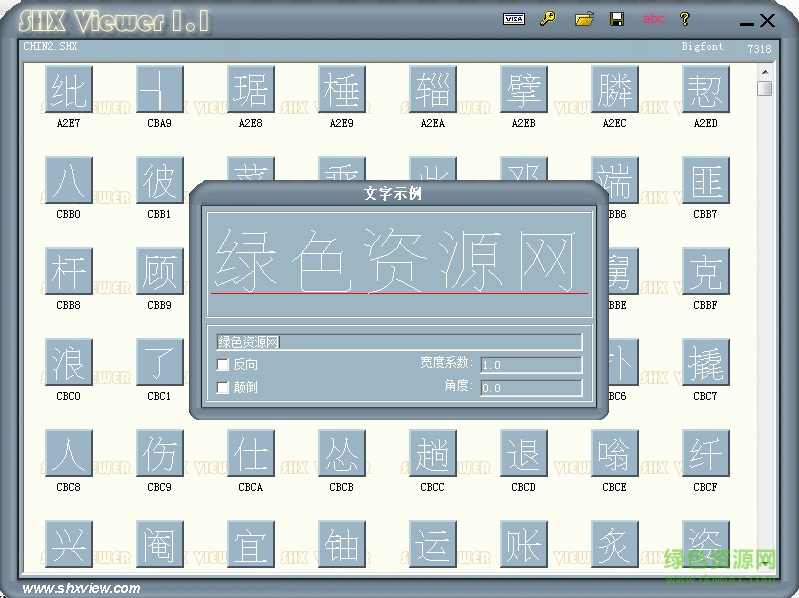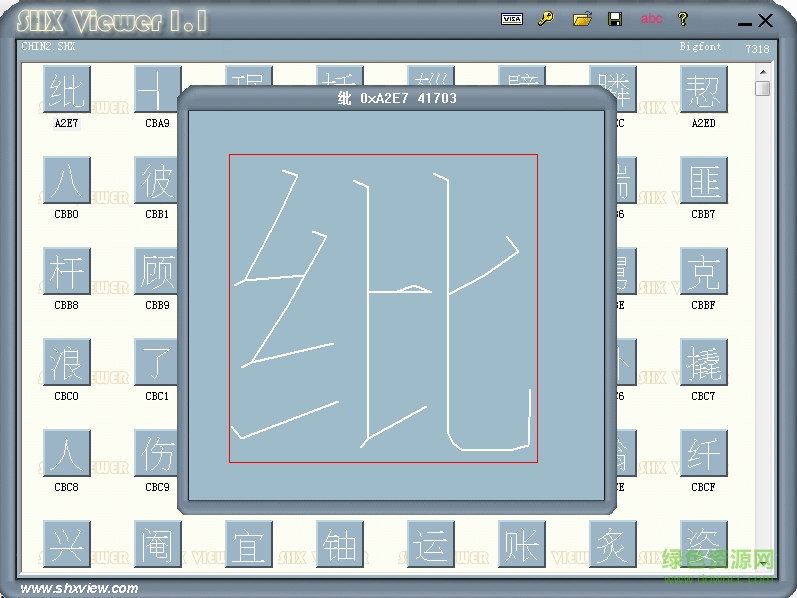
chin2.shx是一款字跡纖秀、簡潔舒適的cad字體,讓你的設(shè)計充滿干凈優(yōu)雅的視覺體驗(yàn),喜歡的朋友來綠色資源網(wǎng)免費(fèi)下載吧!
chin2.shx支持中文輸入,安裝適用于autocad軟件,清新簡約的筆觸深顯造型干練流利之美,適用于平面設(shè)計、創(chuàng)意設(shè)計等領(lǐng)取。
cad里所稱的shx字體和大字體(也叫bigfont),都是autocad自己專用專有的字體。大字體也是shx字體,是shx字體的一種特殊形式。要說shx字體,還得說說字體在cad里的發(fā)展過程。